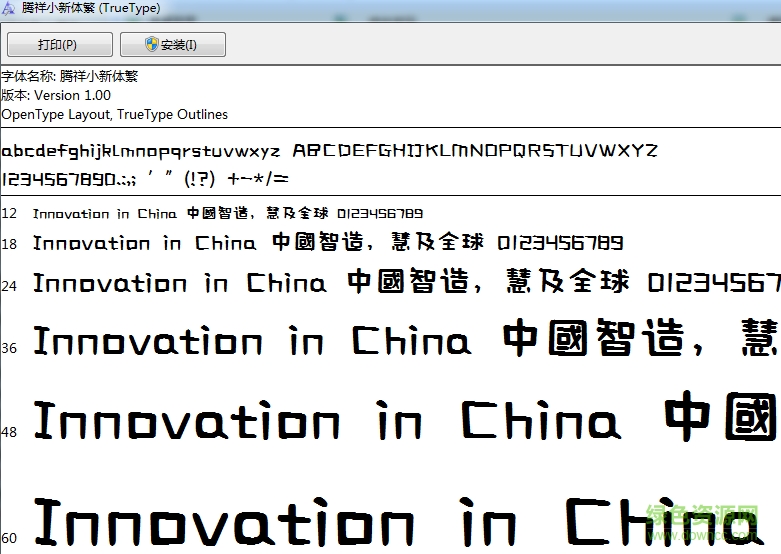
軟件介紹 軟件標簽: 其他字體 字體 騰祥小新體繁字體是騰祥字體庫中的一款繁體字體,字體非常萌,小新體看到就有一種蠟筆小新的感覺,對于喜歡個性的朋友來說這款字體非常適合,。有需要的朋友就來綠色資源網下載吧!騰祥小新體繁字體安裝方法方法一:控制面板/字體/文件/安裝新字體;方法二:直接將字體復制到C:\WINDOWS\Fonts。方法三:針對win7系統(tǒng),用戶只需選中字體右鍵安裝即可。注意事項本站所有字體資源僅供個人學習與參考,如需商業(yè)使用請到相關官網授權。小編測評騰祥小新體繁字體是一款繁體中文字體,字體的字型十分出色,給人一種過目難忘的感覺,有需要的朋友就趕快來綠色資源網下載吧! 軟件截圖 上一張下一張(1 / 1) 安裝詳細截圖 猜你喜歡 騰祥字體 騰祥字體 騰祥字體(Tensentype)是由騰祥公司推出的一系列字體合集,開發(fā)推出了多款特色字體,如:騰祥嘉麗中黑簡、騰祥金磚黑簡、騰祥潮黑等,每款字體都很有特點,獨具個性,深受廣大朋友們的喜愛。 查看更多>> 騰祥豆豆體簡繁 8.78M/中文/5.0/v1.0 pd端下載 騰祥泡泡體ttf 5.89M/中文/5.0/下載 tensentype chaoheij字體 1.34M/中文/5.0/下載 tensentype xiangsif 2.44M/中文/5.0/下載 tensentype jinzhuanheij 2.44M/中文/3.3/下載 騰祥匆匆體繁 4.98M/中文/5.0/下載 其他版本下載 標題 大小 更新日期 下載 下載地址 電腦版 騰祥小新體繁 點擊報錯 軟件無法下載或下載后無法使用,請點擊報錯,謝謝! 關閉報錯反饋 請描述您所遇到的錯誤,我們將盡快予以修正,謝謝! *必填項,請輸入內容 本類最新 dreamweaver字體庫 首爾南山體字體 v1.06 官方版 潮字社風云簡ttf 潮字社凌渡鯤鵬簡體字體 潮字社曾玉波手書簡字體 微博慧心字體 相關文章 Photoshop字體安裝使用方法和技巧 如何解決“無法新增字體”問題 Win 7系統(tǒng)安裝字體方法 網頁字體大小設置方法 怎么改網頁字體大小 在Linux系統(tǒng)中安裝字體的幾種方法 windows7字體顯示問題:打開某些程序的時候顯示的是亂碼 用戶評論 熱門評論 最新評論 發(fā)表評論 查看所有評論(0) 昵稱: 請不要評論無意義或臟話,我們所有評論會有人工審核. 字數(shù): 0/500 (您的評論需要經過審核才能顯示)